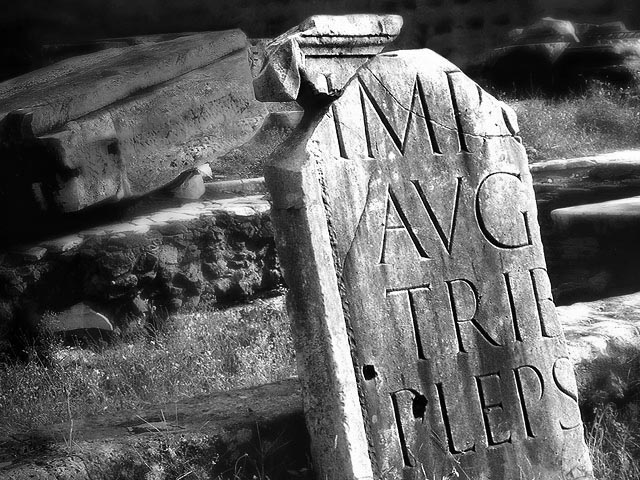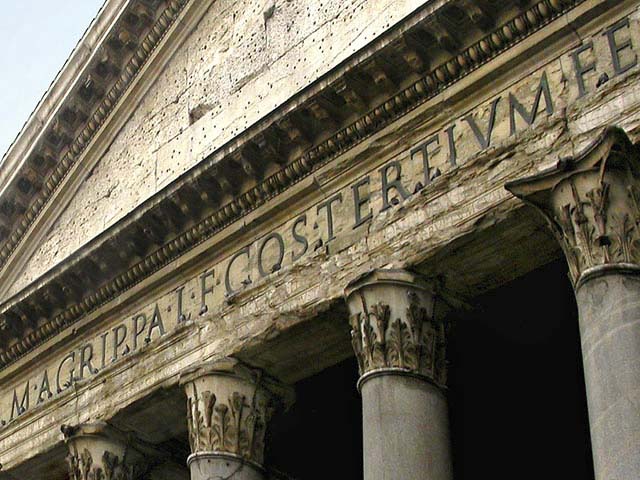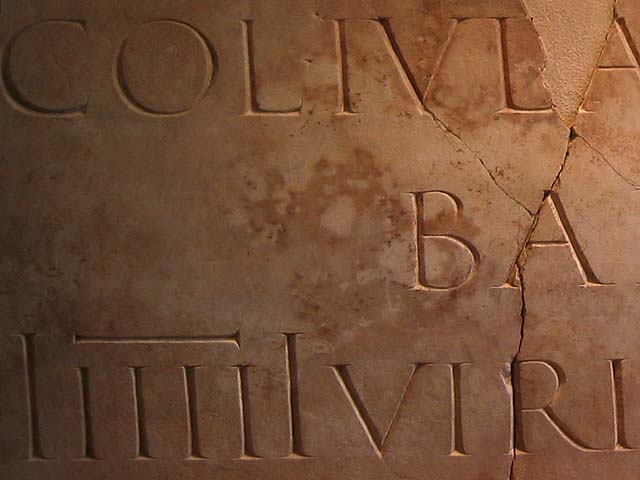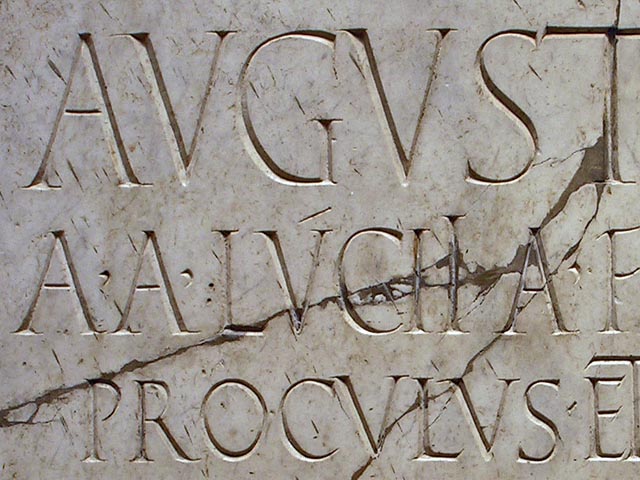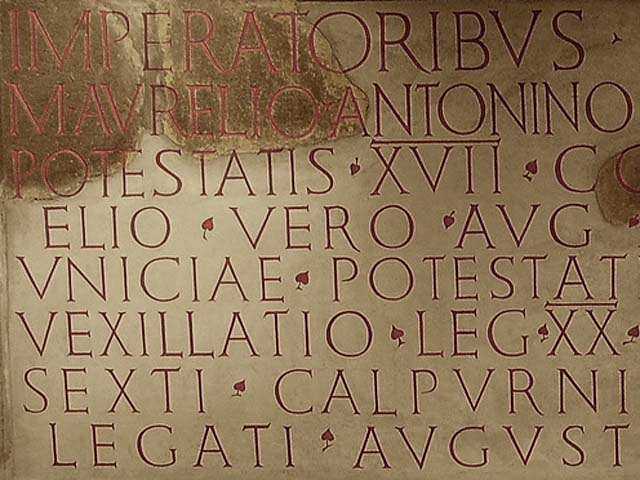
As letras dos Romanos: serifas
No alfabeto latino, as serifas assumem formas refinadas.Inicialmente, as letras romanas escreviam-se (ou esculpiam-se) sem acabamentos terminais e com hastes de grossura regular; só gradualmente, com o aperfeiçoamento das ferramentas para trabalhar a pedra, é que se desenvolveram as terminações designadas por patilhas ou serifas. Quando passou a usar serifas, a letra romana também mostrou contrastes na grossura de traço. No século i a.n.E, finalizando uma lenta evolução de 700 anos, os romanos usavam um alfabeto versal muito semelhante ao nosso, no qual faltavam apenas as letras J, V, W e Z. Para gravar letras em pedra, os artesãos romanos primeiro pintavam os traços com um pincel, talvez com algum auxílio da régua e do compasso, mas sem o rigor de esquemas numéricos. No Império Romano não existiam cânones universais para o desenho de inscrições nem para a forma das letras, as suas proporções, a grossura do traço, o ângulo de inclinação, o desenho das serifas ou a profundidade do corte na pedra.